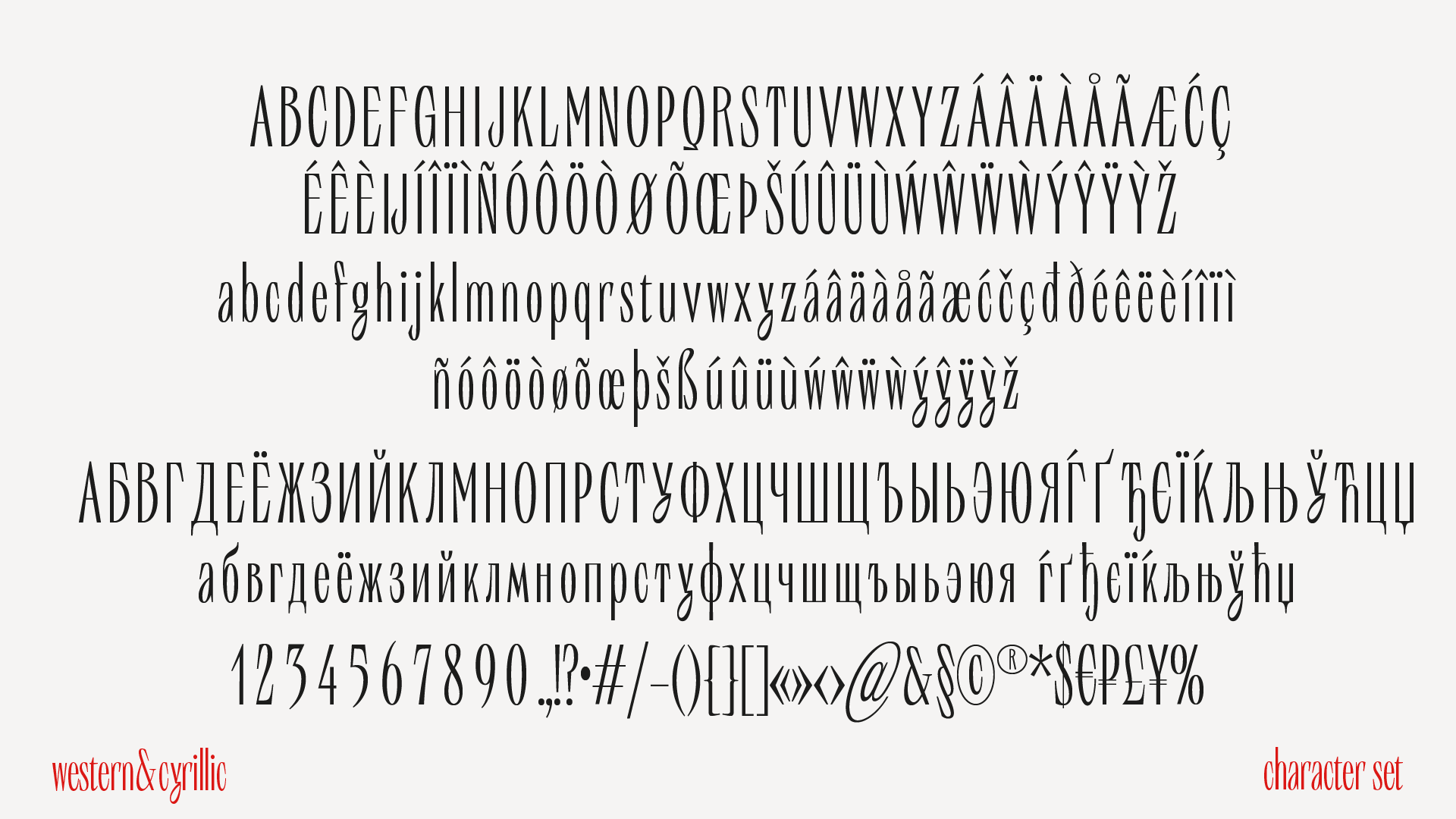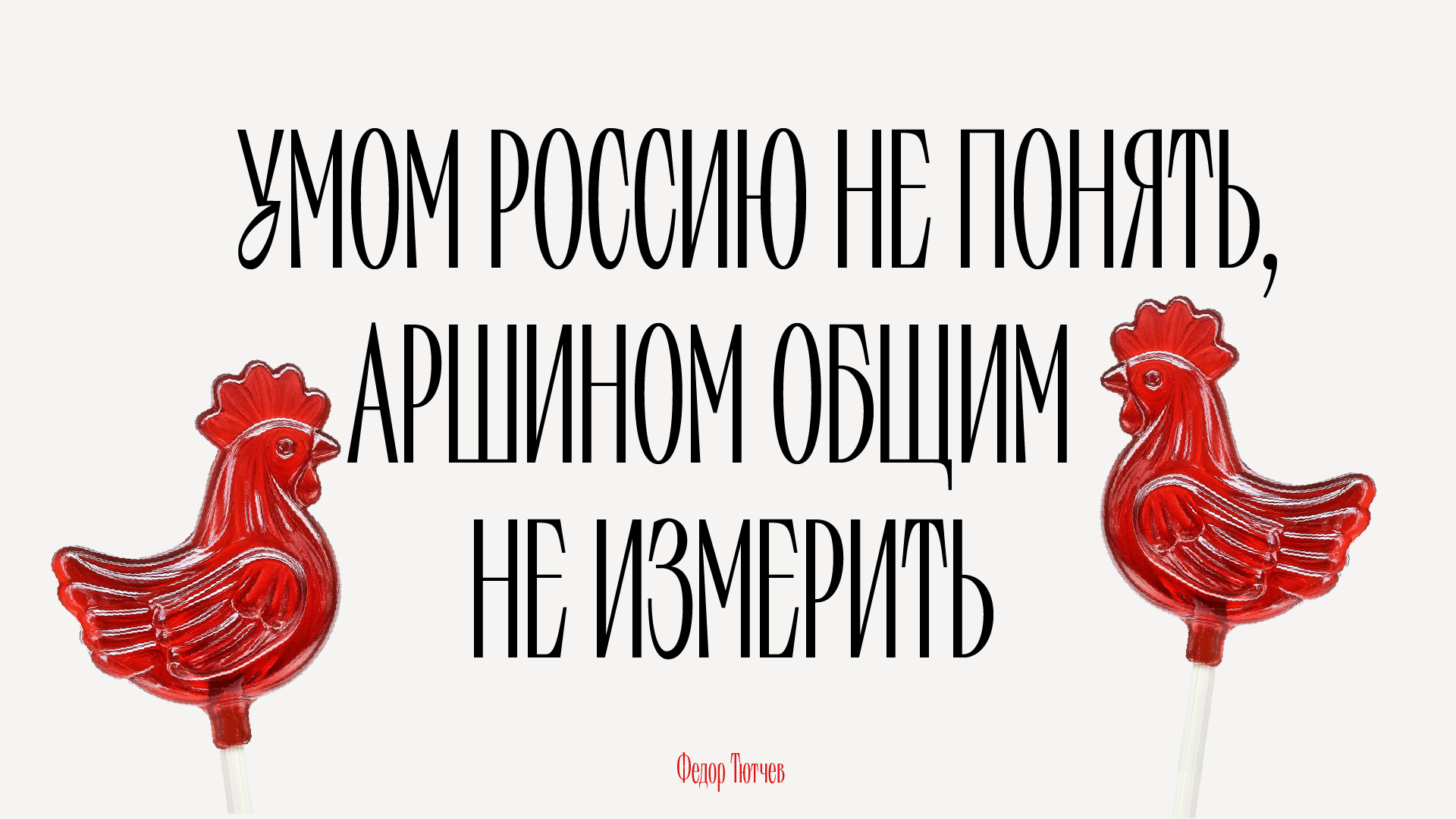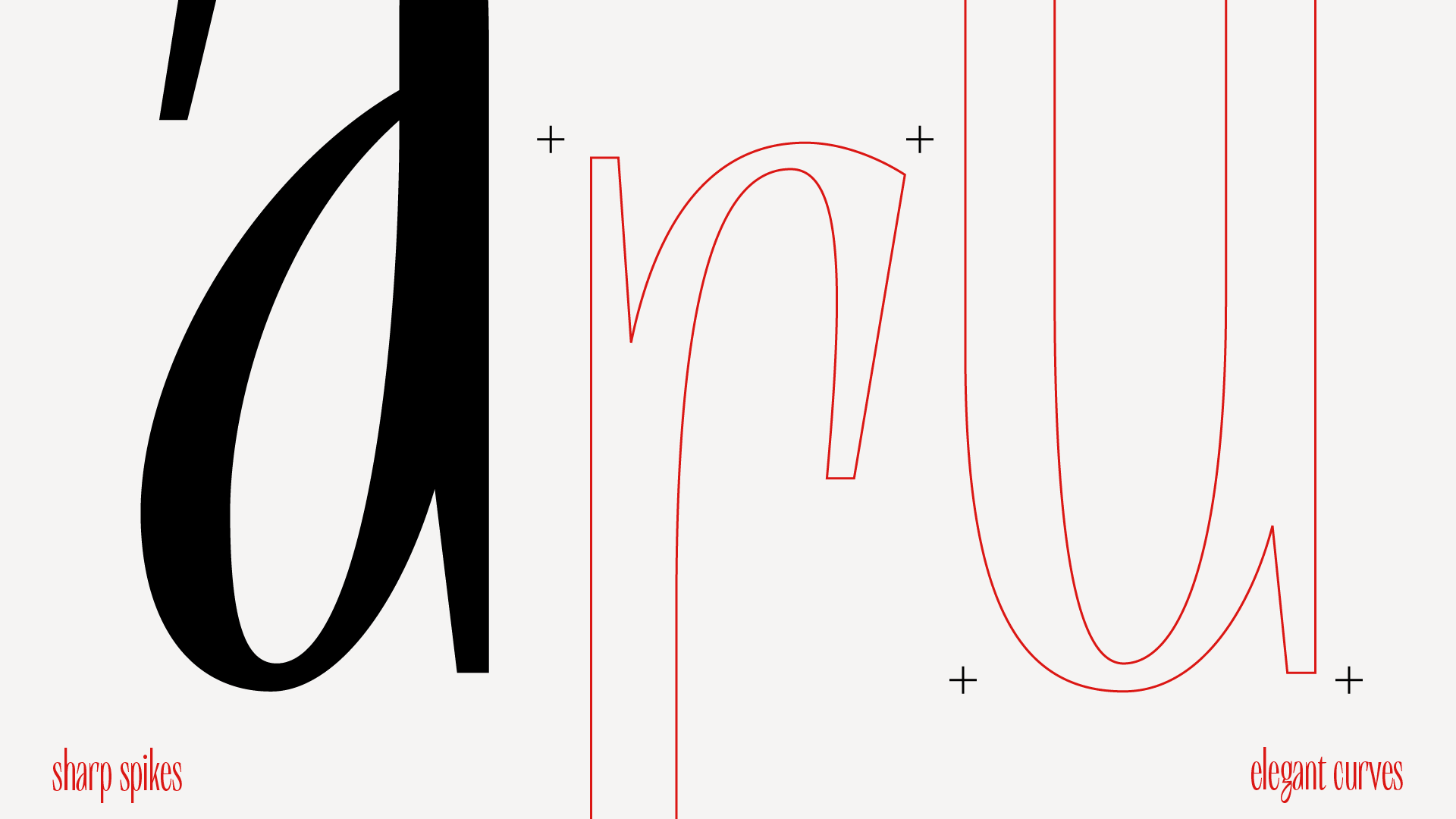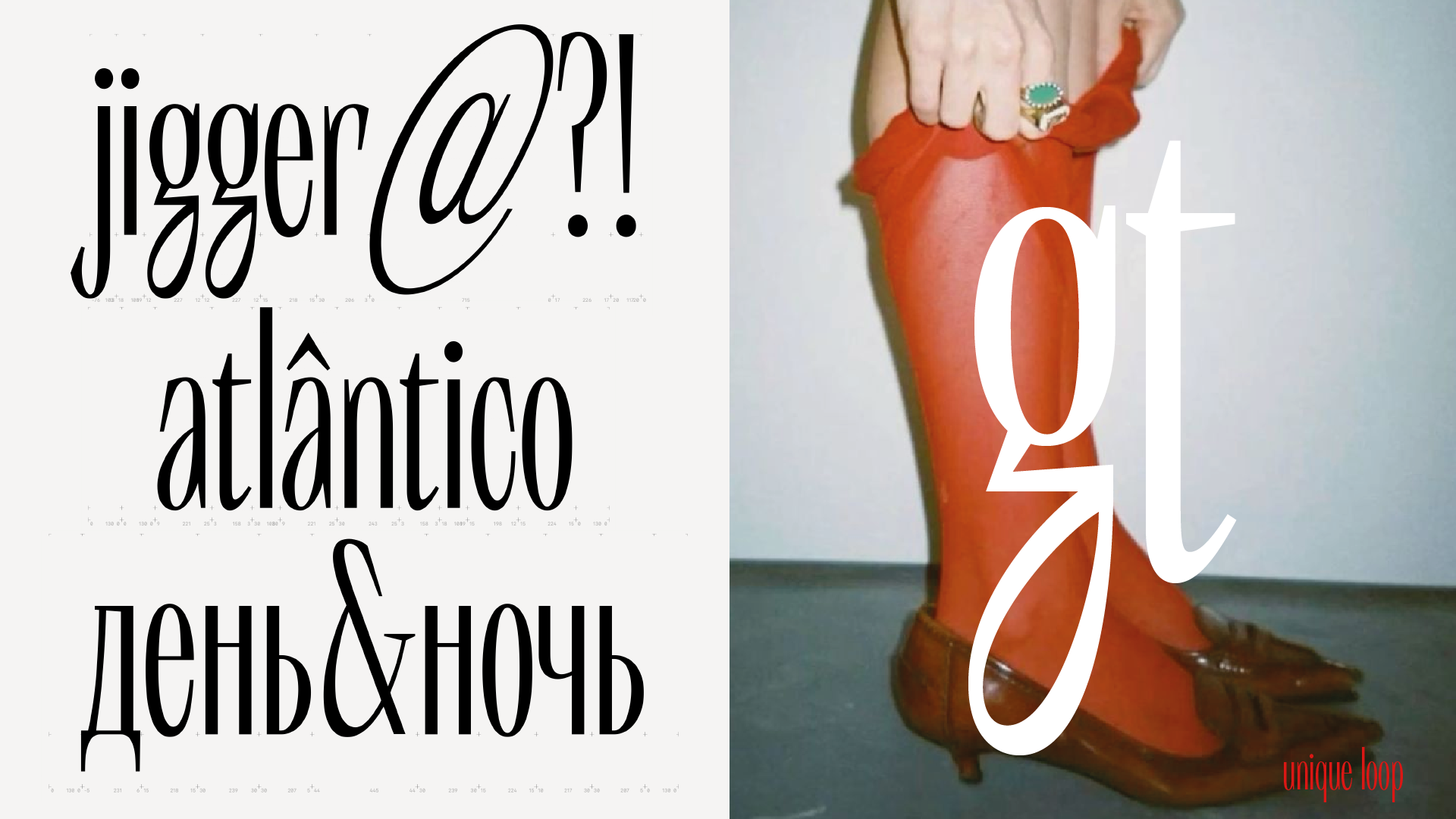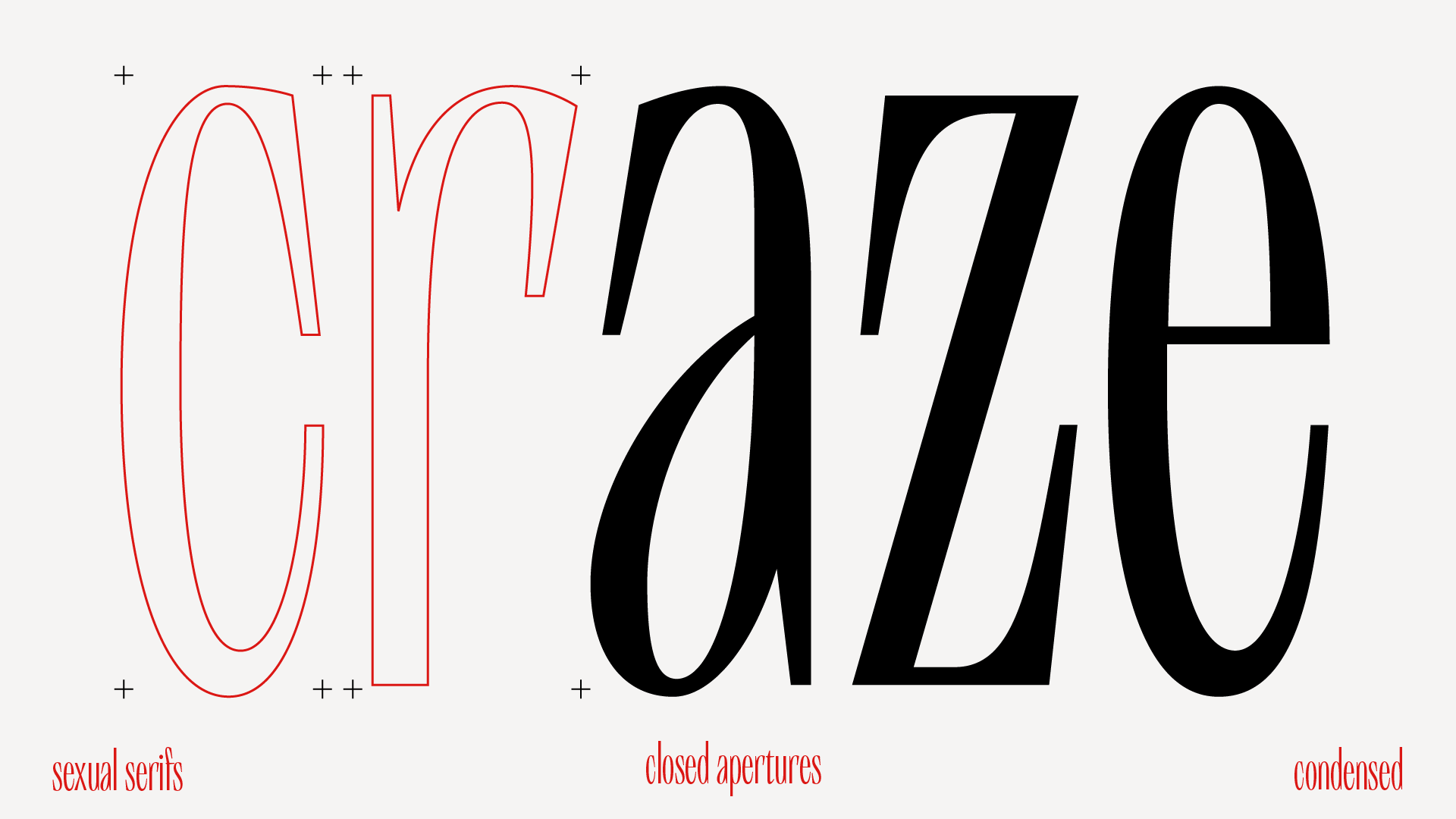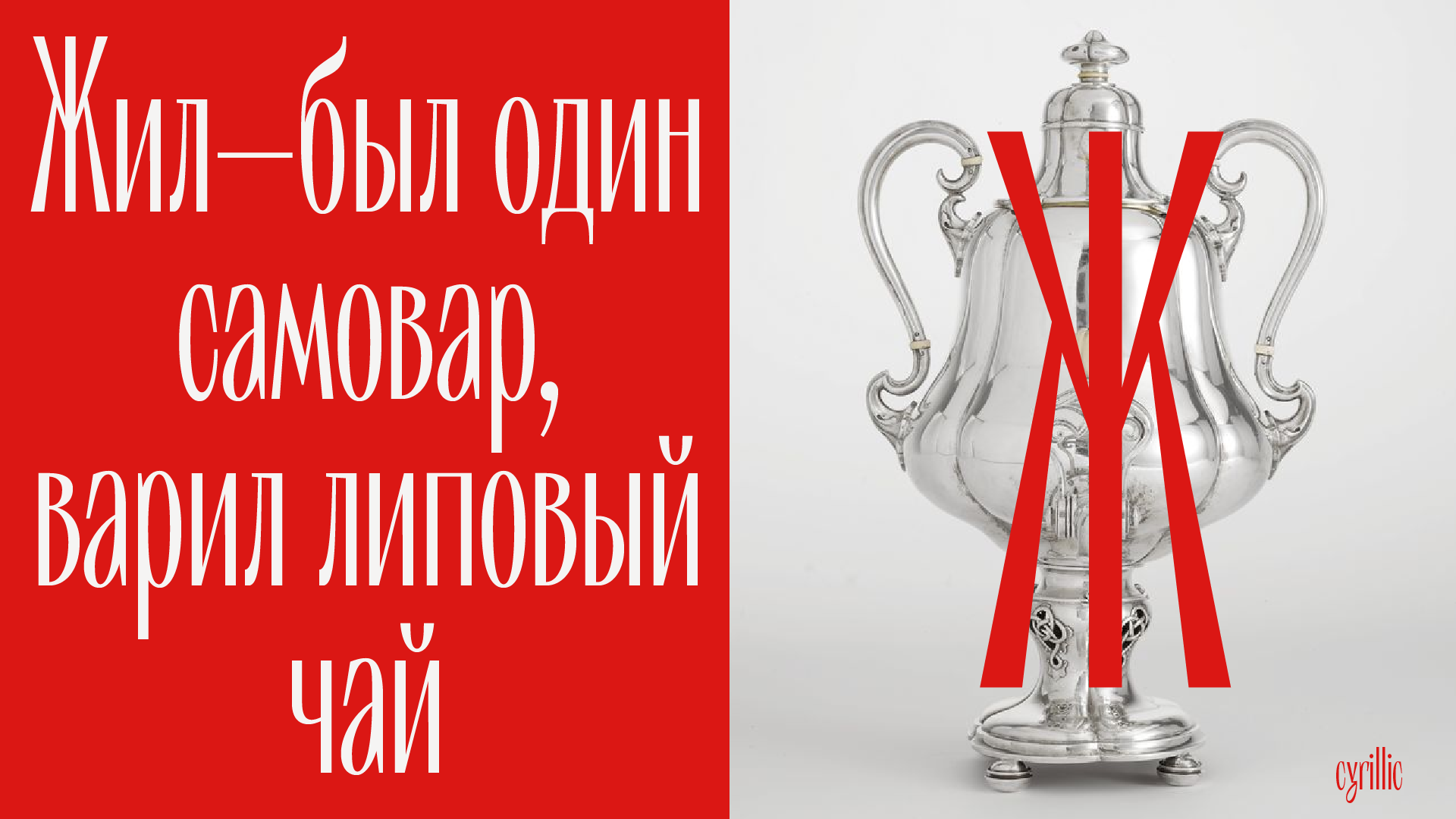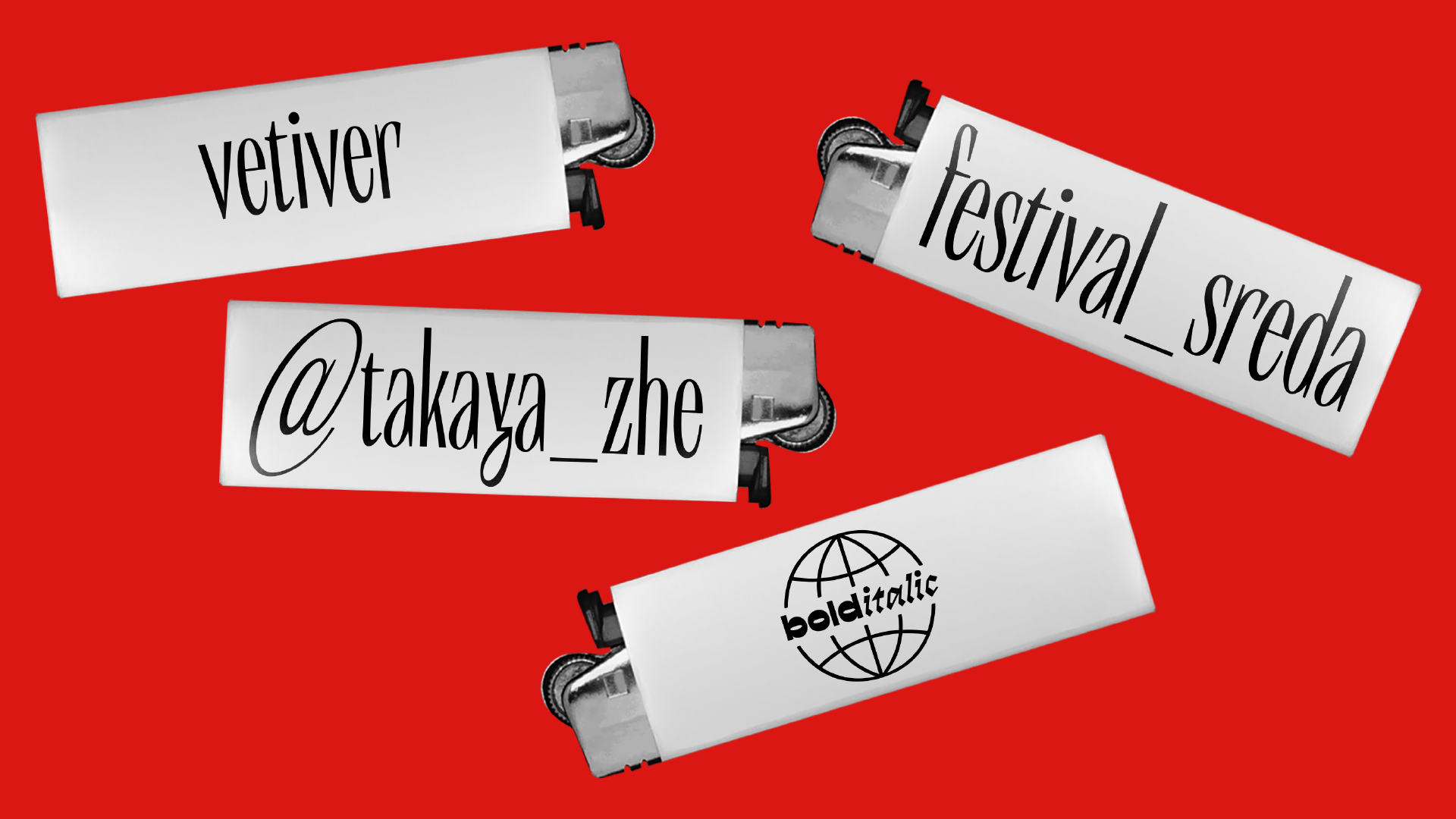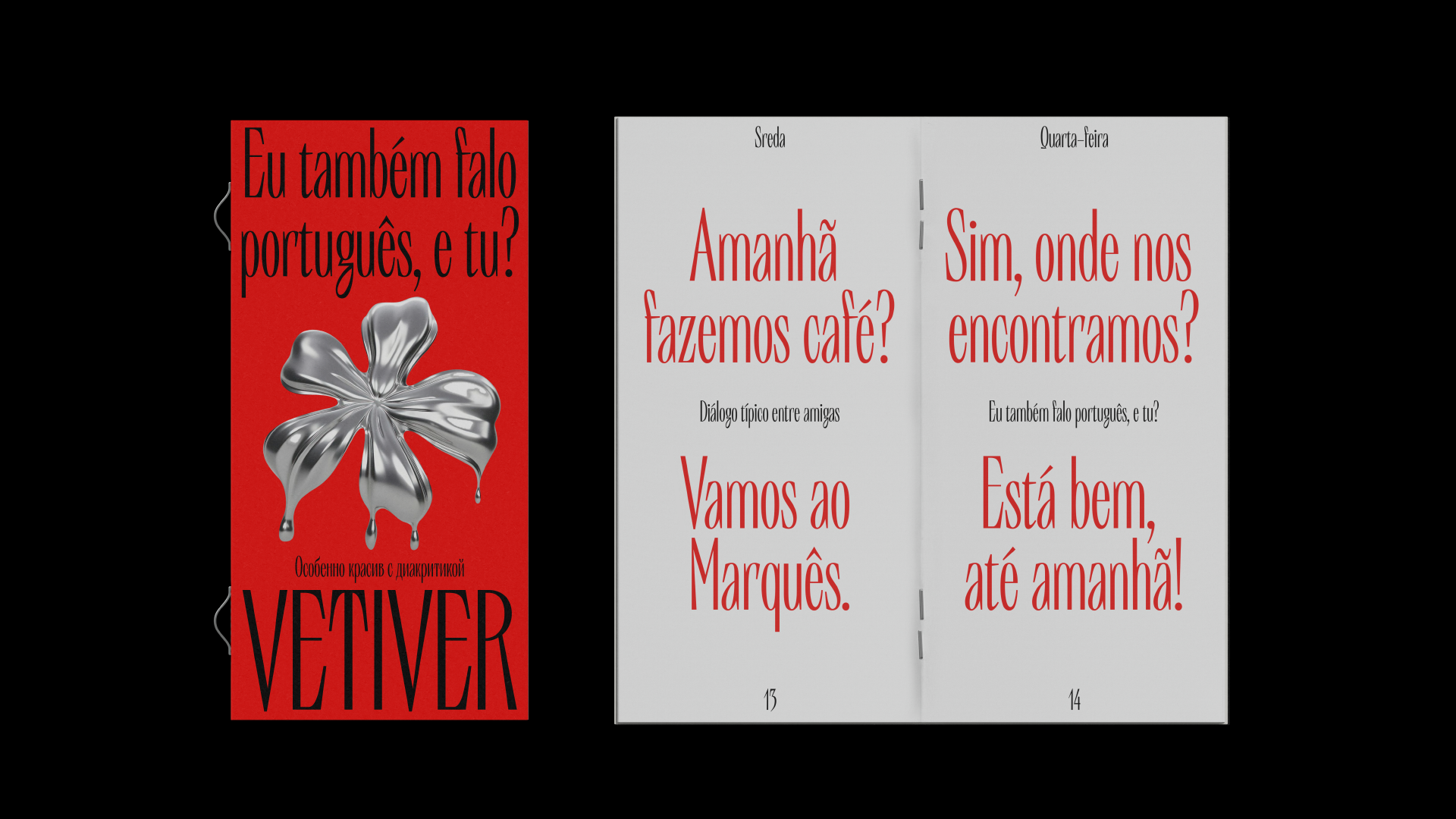
Vetiver
Акцидентная ленточная антиква с высоким контрастам и закрытыми апертурами. Шрифт создан для набора в крупном кегле.
Шипами и засечки в шрифте задают звонкий и колкий характер.